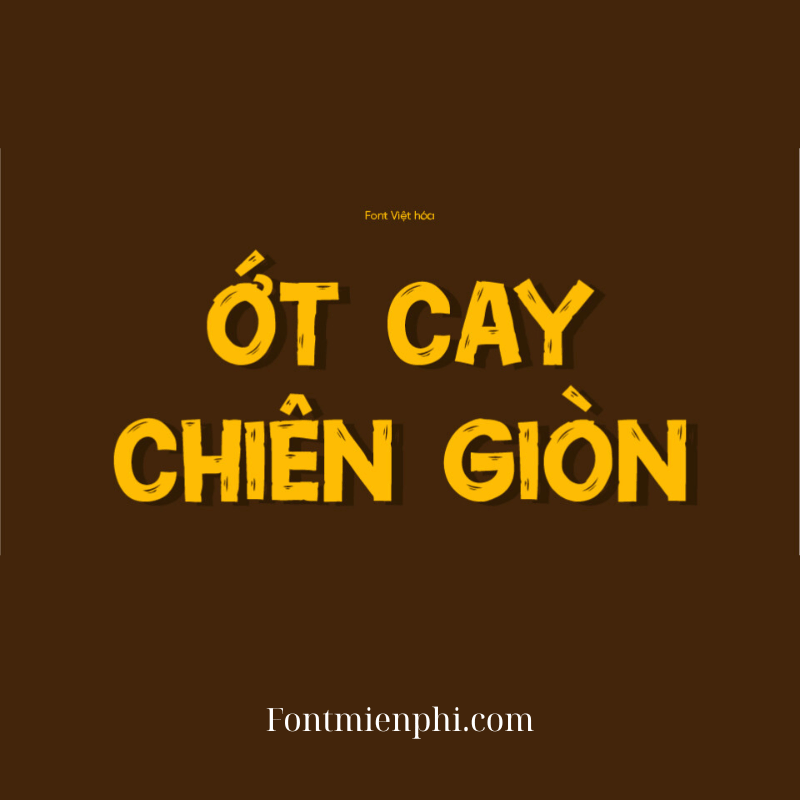
Font Việt hóa 1FTV VIP Potato Chips
Font Việt Hóa 1FTV VIP Potato Chips – Phong Cách Độc Đáo Cho Thiết Kế
Giới Thiệu
Font Việt hóa 1FTV VIP Potato Chips là bộ font chữ sáng tạo, độc đáo, được thiết kế dành riêng cho cộng đồng yêu thích typography tiếng Việt. Với phong cách “khoai tây chiên” vui nhộn, font chữ này mang đến sự mới lạ, phù hợp cho các dự án thiết kế poster, logo, banner hoặc nội dung mạng xã hội.
Đặc Điểm Nổi Bật
• Thiết kế độc quyền: Nét chữ bo tròn, đáng yêu, tạo cảm giác gần gũi và thu hút.
• Hỗ trợ tiếng Việt đầy đủ: Bao gồm cả dấu câu và ký tự đặc biệt, phù hợp với mọi nhu cầu thiết kế.
• Đa dạng ứng dụng: Dùng cho in ấn, quảng cáo, game, hoặc thiết kế đồ họa.
Lợi Ích Khi Sử Dụng
Font 1FTV VIP Potato Chips giúp sản phẩm thiết kế của bạn trở nên khác biệt, tăng tính nhận diện thương hiệu. Font chữ dễ đọc, phù hợp với nhiều phong cách từ trẻ trung đến cá tính.
Kết Luận